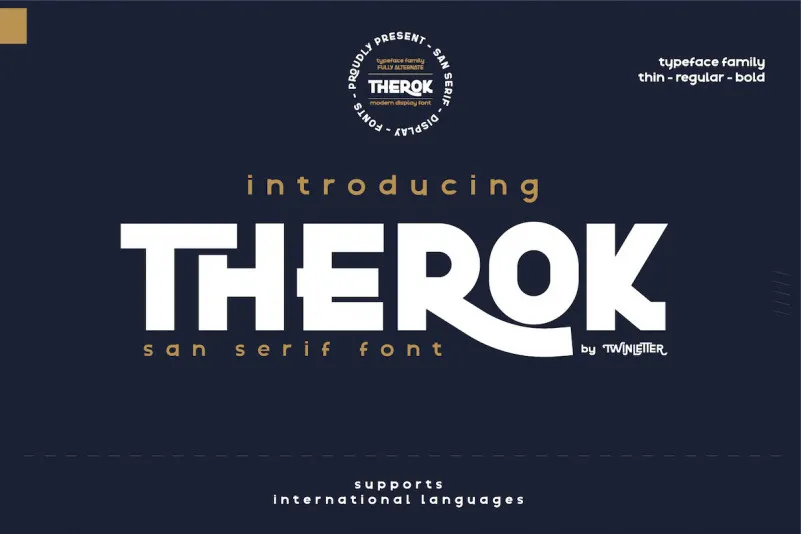
Therok Font – Fonte Grátis
Therok Font
Esta font é perfeitamente adaptada para projetos que exigem impacto e destaque, tornando-a uma escolha excelente para diversos tipos de mídia visual. Suas linhas retas e diretas oferecem uma forte identidade visual ideal para aplicações como jogos, eventos esportivos, publicidade, banners, outdoors, títulos de filmes, estilos de roupas, logotipos e muito mais. Com seu design sem serif, o Therok Font se destaca em ambientes tecnológicos, texturas culinárias e bebidas, expressões visuais para mensagens impactantes e até mesmo em criações artísticas. Este recurso gráfico é uma excelente adição à sua biblioteca de fontes, permitindo que você faça um impacto visual notável nas suas publicações digitais e impressas.